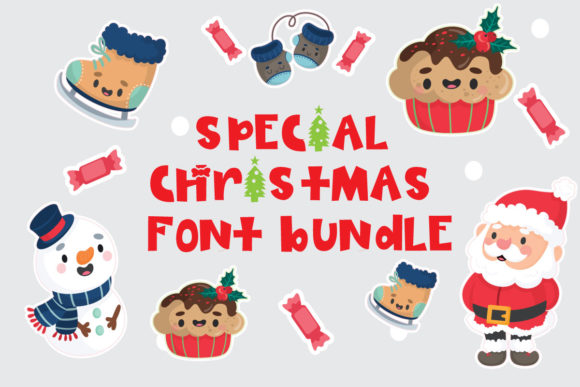
Special Christmas Font Bundle
Die richtigen Designelemente zu finden, kann eine Herausforderung sein, aber Special Christmas Font Bundle bietet eine außergewöhnliche Sammlung, die Ihre Arbeit sofort aufwertet.
Egal, ob Sie POD-Produkte (Print on Demand), Hochzeitseinladungen oder Social-Media-Grafiken erstellen, Special Christmas Font Bundle ist die ideale Wahl.